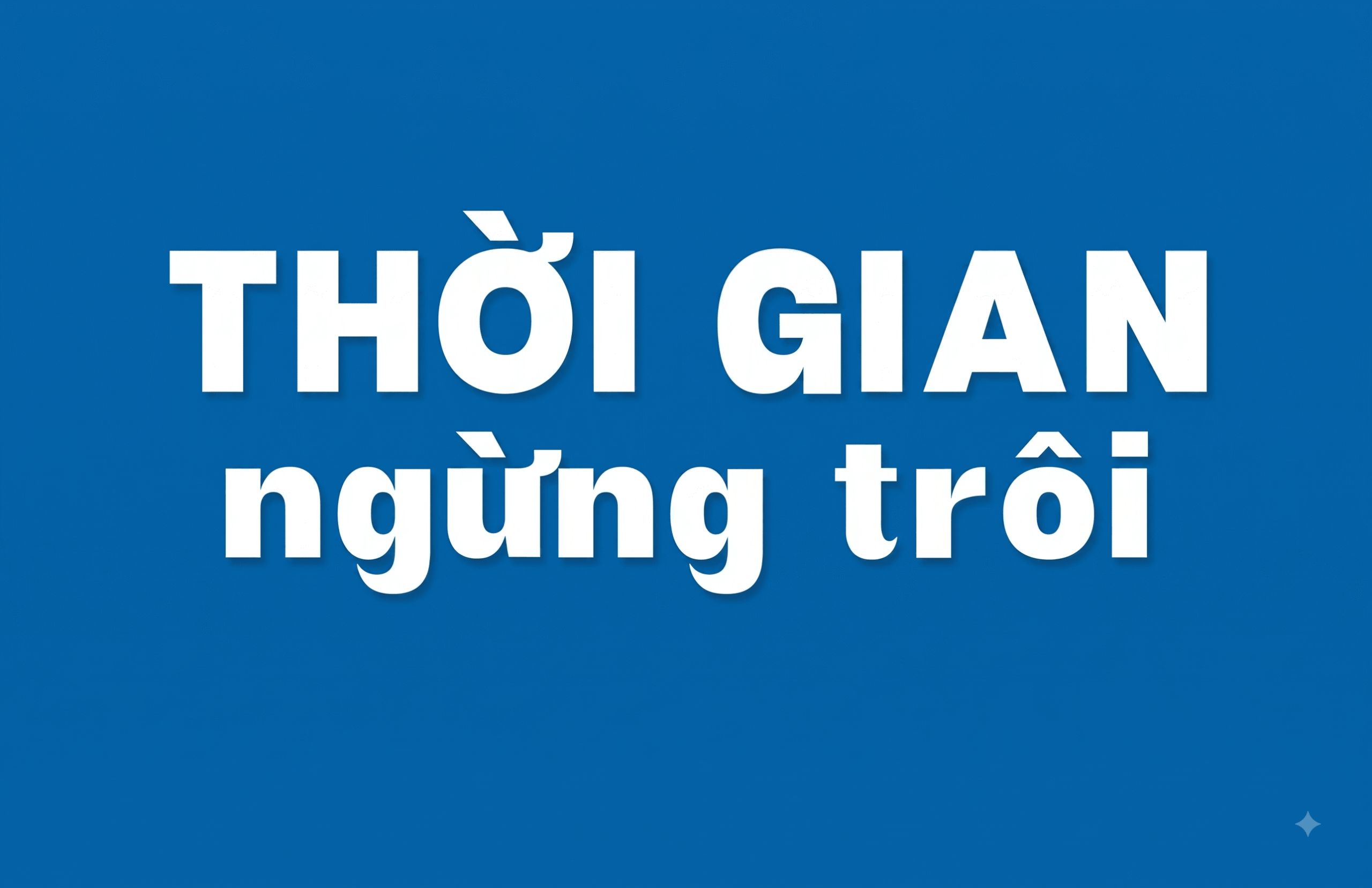
Font Việt hóa 1FTV VIP Bright Giftak là một lựa chọn tuyệt vời dành cho các nhà thiết kế
Giới Thiệu Font Việt Hóa 1FTV VIP Bright Giftak
Font Việt hóa 1FTV VIP Bright Giftak là một lựa chọn tuyệt vời dành cho các nhà thiết kế đang tìm kiếm sự mới mẻ, thanh lịch và nổi bật. Với những đường nét được chăm chút tỉ mỉ, bộ font này mang đến cảm giác hiện đại nhưng không kém phần mềm mại, rất phù hợp cho các dự án mang tính cá nhân hóa cao. Quá trình Việt hóa chuẩn xác giúp các dấu tiếng Việt hiển thị mượt mà, không bị lỗi phông hay lệch khoảng cách ký tự.
Đặc Điểm Nổi Bật Của Bộ Font
Việc lựa chọn một phông chữ cao cấp không chỉ nằm ở kiểu dáng mà còn ở tính ứng dụng và độ hoàn thiện. Dưới đây là những ưu điểm vượt trội của bộ phông chữ này:
• Đường nét tinh tế: Thiết kế hài hòa, độ dày mỏng linh hoạt tạo điểm nhấn thị giác mạnh mẽ.
• Việt hóa chuẩn xác: Các dấu câu tiếng Việt (kerning, accent) được tinh chỉnh kỹ lưỡng, đảm bảo tính thẩm mỹ trên mọi kích thước văn bản.
• Khả năng hiển thị tốt: Dễ đọc và sắc nét trên cả ấn phẩm in ấn lẫn các giao diện kỹ thuật số.
Ứng Dụng Thực Tế Trong Thiết Kế
Sự đa dụng của 1FTV VIP Bright Giftak giúp bộ font này dễ dàng tỏa sáng trong nhiều lĩnh vực sáng tạo khác nhau:
• Thiết kế bao bì & Quà tặng: Đúng như tên gọi “Bright Giftak”, đây là lựa chọn hoàn hảo cho các nhãn mác, hộp quà và thiệp chúc mừng.
• Nhận diện thương hiệu: Phù hợp làm logo, slogan cho các thương hiệu thời trang, mỹ phẩm hoặc dịch vụ sáng tạo.
• Truyền thông mạng xã hội: Tạo sự thu hút đặc biệt cho các banner quảng cáo, ảnh bìa hoặc typography nghệ thuật.